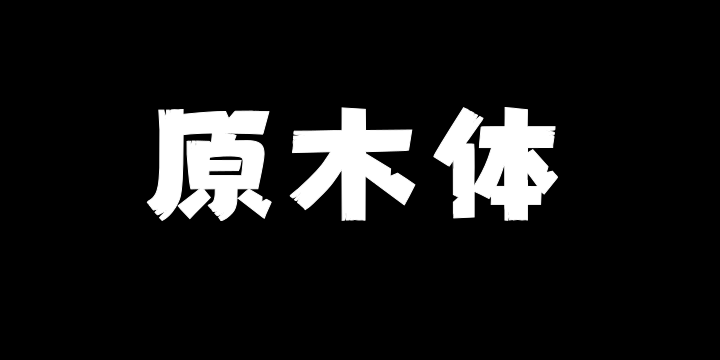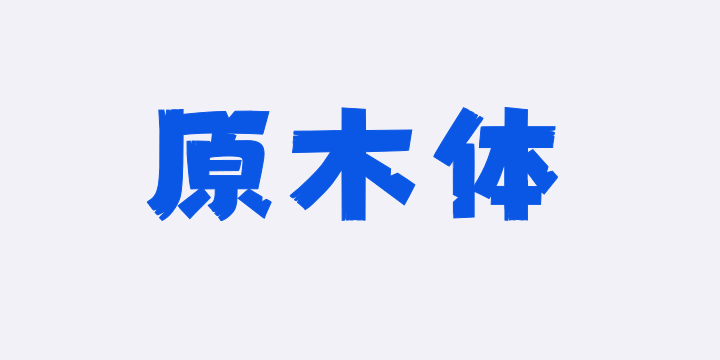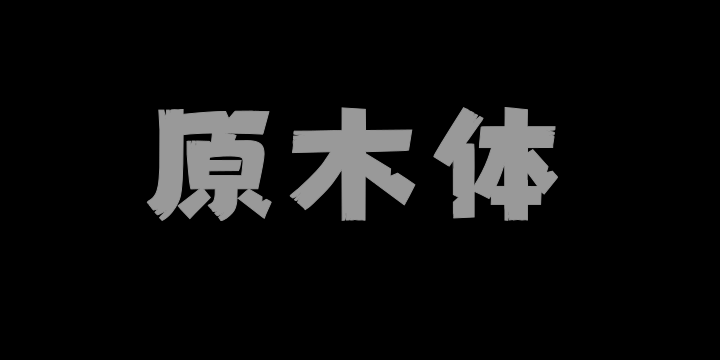
上首原木体 By 上首造字 商用字体
字体全名: 上首原木体
铸字厂: 上首造字
设计师: 胡博剑
字体简介: 上首原木体,简体中文约6763字,字体整体方正,粗细均衡。字体转折处以圆角处理,使得字体整体更加柔和;字体笔画做了适量的木纹、缺口处理,使得字体更具有设计感,同时也使字体拥有一种古朴之感。字体整体柔和、古朴但又不失稳重,适用于搭配标志、广告标语、商业广告、海报字体等高端属性。